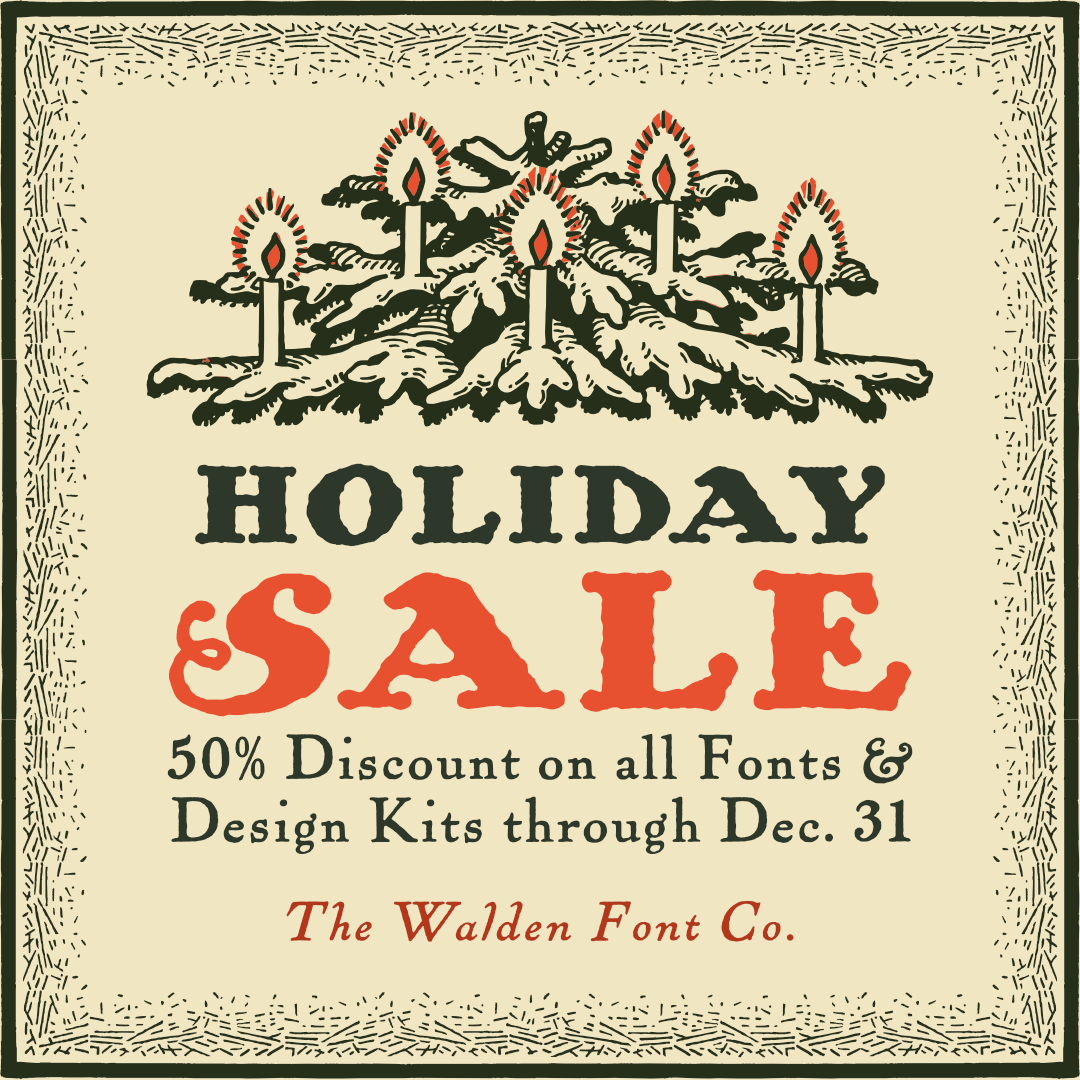
Nicht um in dieselbe Kerbe zu hauen, aber heute morgen habe ich in unter 15 Minuten diese Anzeige zusammengeschustert, und sie gefiel mir so saumäßig, daß ich sie Euch unbedingt reindrücken muß 🙂
Schriften sind WF Border Rauhreif, WF Ohio Kraft und WF Ohio Schrift, alle aus dem Kraftwerk Press Design Kit. Die Kerzen werden in meinem Weihnachtspaket zu haben sein, wenn's fertig ist.
Ich bin mir bewusst, dass Du Dich an historischen Originalen abarbeitest und diese manchmal limitiert sind, aber wäre eine Th-Ligatur und etwas weniger Platz zwischen Wa und Fo (sowohl bei der recta als auch bei der cursiva) angemessener? Die Anzeige ist so hübsch, dass mir das sowas von ins Auge gesprungen ist... 🙂
Da hast Du ganz recht. Die Zurichtung bei der Ohio entspricht dem Original. Heutigen Erwartungen reicht das nicht; da muß ich vielleicht nochmal ran.
Mich irritieren die Großbuchstaben in der Subline – sie wirken fetter als die Kleinbuchstaben. Im Englischen ist das auch nicht weiter dramatisch aber im Deutschen fällt so etwas schon auf. Aber man muss ja auch nicht alles glattbügeln.
Für die Gill gab es zu Bleisatzzeiten beispielsweise angepasste Versalien die nicht so hervorstachen – sowas ließe sich ja heute gut über OT-Features je nach Sprache lösen.
Das sehe ich bei älteren Schriften recht oft, und manchmal sehr dramatisch, fast als hätte man die Großbuchstaben als "separat-harmonierend" empfunden. Auch habe ich neuzeitliche Artikel gelesen, in denen gegen überraffinierte Zurichtung gewettert wird, à la "Gebt den Großbuchstaben Luft, sie sollen wirken!"
Die gemischte Schreibweise ist ja recht jung und auch international begrenzt. Gebrauche ich eine Versalie, habe ich damit auch ein wichtiges Wort, dass auch etwas auffällig aus der Bleiwüste ragen darf.
So, jetzt können wir gerne weiter über übermächtige Versalien reden: Mir geht es bei manchen Caslons so, dass ich deren Majuskeln für den deutschen Satz als zu wuchtig empfinde.
Im Englischen passt das für mich auch in den meisten Fällen. Im Deutschen kann es dann aber schon etwas unruhig werden ...
Ganz richtig, und gerade fällt mir auf, daß dieses Phänomen bei angelsächsischen Schriften auftritt. Die Ohio ist ja eine minimal angepaßte Pabst Oldstyle,  das macht also Sinn.
Mir ist das vor allem bei einigen  Kursiven aufgefallen, da differieren die Neigungswinkel recht üppig.
Dass die Neigungswinkel innerhalb kursiver Schriften differieren, ist richtig und notwendigerweise der Optik geschuldet.
Stark vereinfacht gesagt: Glyphen mit Oberlänge sind je nach Schriftart und Design weniger schräg gestellt als Buchstaben mit x-Höhe.
Versalien haben mitunter merklich weniger Schräglage.
Am Beispiel der kursiven Garamond ist dies sehr klar zu sehen, wenn man sie vergrößert.
Ich hatte mir heute zum Ziel gesetzt, die Zurichtung der Ohio zu überarbeiten. Dabei stellte sich heraus, daß ich auf meinem Mac eine Experimentalversion ohne jegliche Zurichtung installiert hatte 🙄 Die auf meiner Website erhältliche Version ist dagegen in bester Ordnung.
Wo ich aber mal dabei war, habe ich verschiedene Änderungen an den Schriften vorgenommen, denn seit 2016 habe ich ordentlich dazugelernt. Es kommt also in Bälde ein Update.
Es sind übrigens nicht nur anglo-amerikanische Schriften mit "zu fetten" Versalien ausgestattet, sondern auch große europäische Bleisatz-Klassiker wie die Van Dijck oder die Nicolas Cochin. Gefällt mir auch bei Anwendung mit deutschsprachigen Texten trotzdem meist ganz gut ...